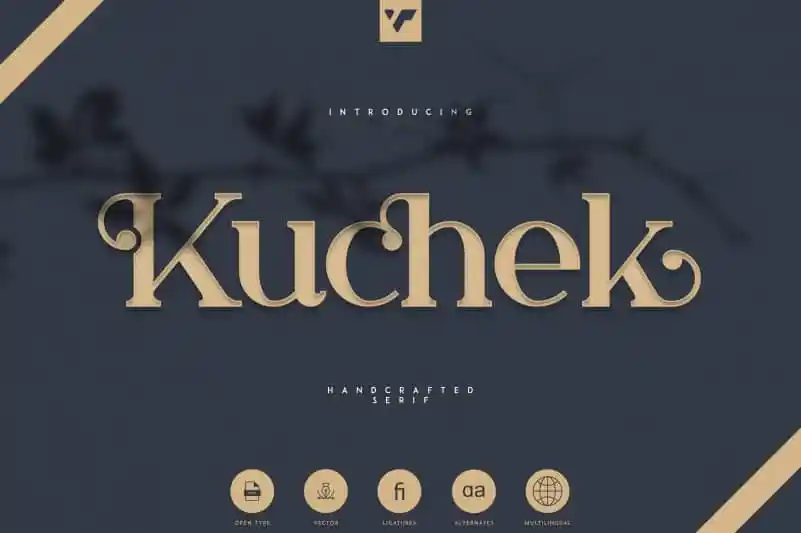
Kuchek - Handcrafted Serif Font
Kuchek é uma elegante e vintage font serif que oferece um blend harmonioso entre formas antiguinhas e linhas modernas. Este tipo-fonte contém um vasto conjunto de caracteres, incluindo as letras básicas do latim, os detalhes avançados do latim, o Cyrillic básico e o Cyrillic avançado, tornando-o uma opção versátil para designers em busca de um estilo serif que se destaca. Com seu design cuidadosamente elaborado por vp_creative_shop, Kuchek é perfeito tanto para textos legíveis quanto para criações decorativas, trazendo uma atmosfera vintage ao mesmo tempo sofisticada e contemporânea. O resultado é uma fonte que combina elegância com funcionalidade, tornando-se um recurso indispensável para quem procura personalizar projetos de design gráfico com classe.